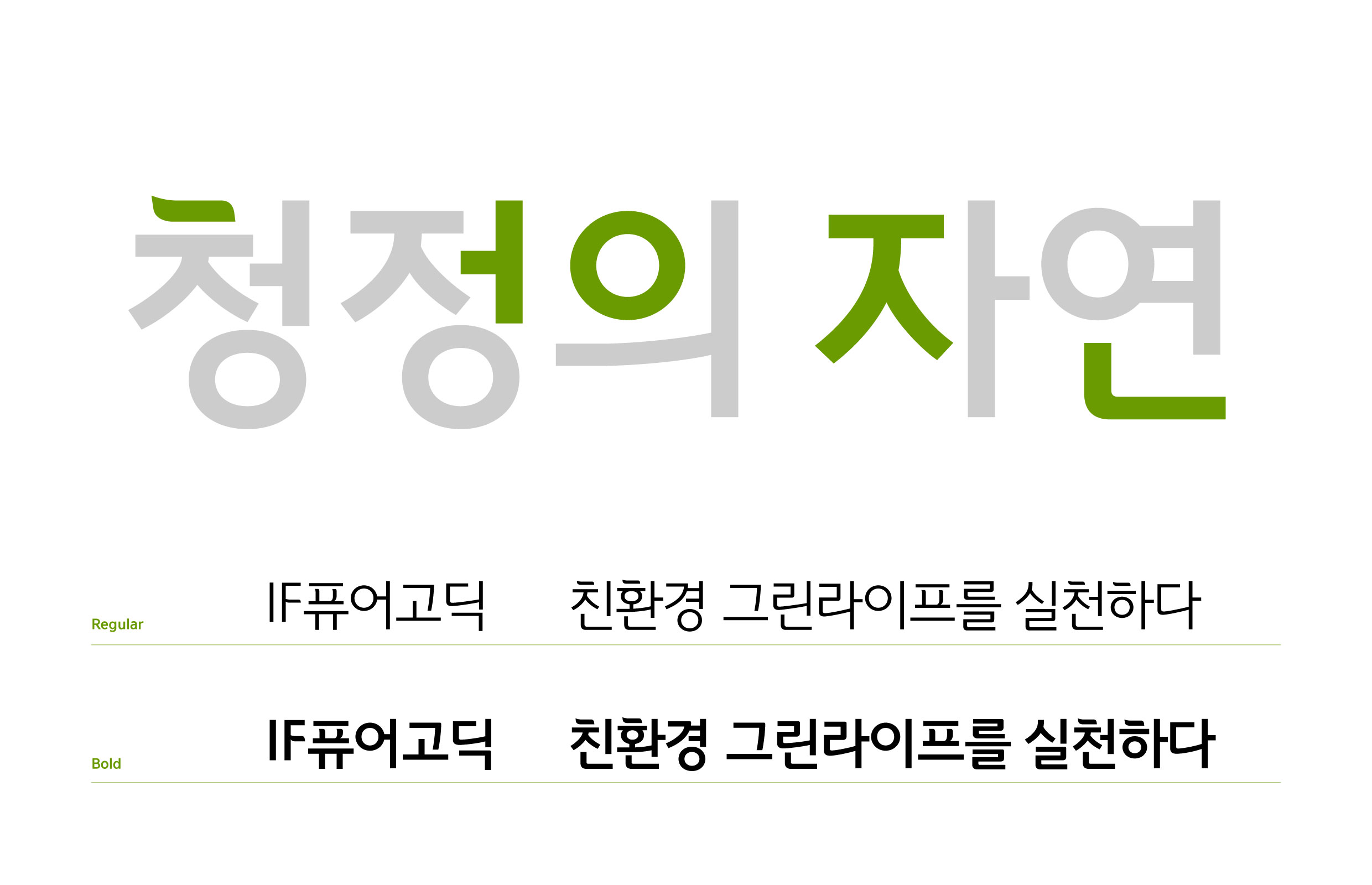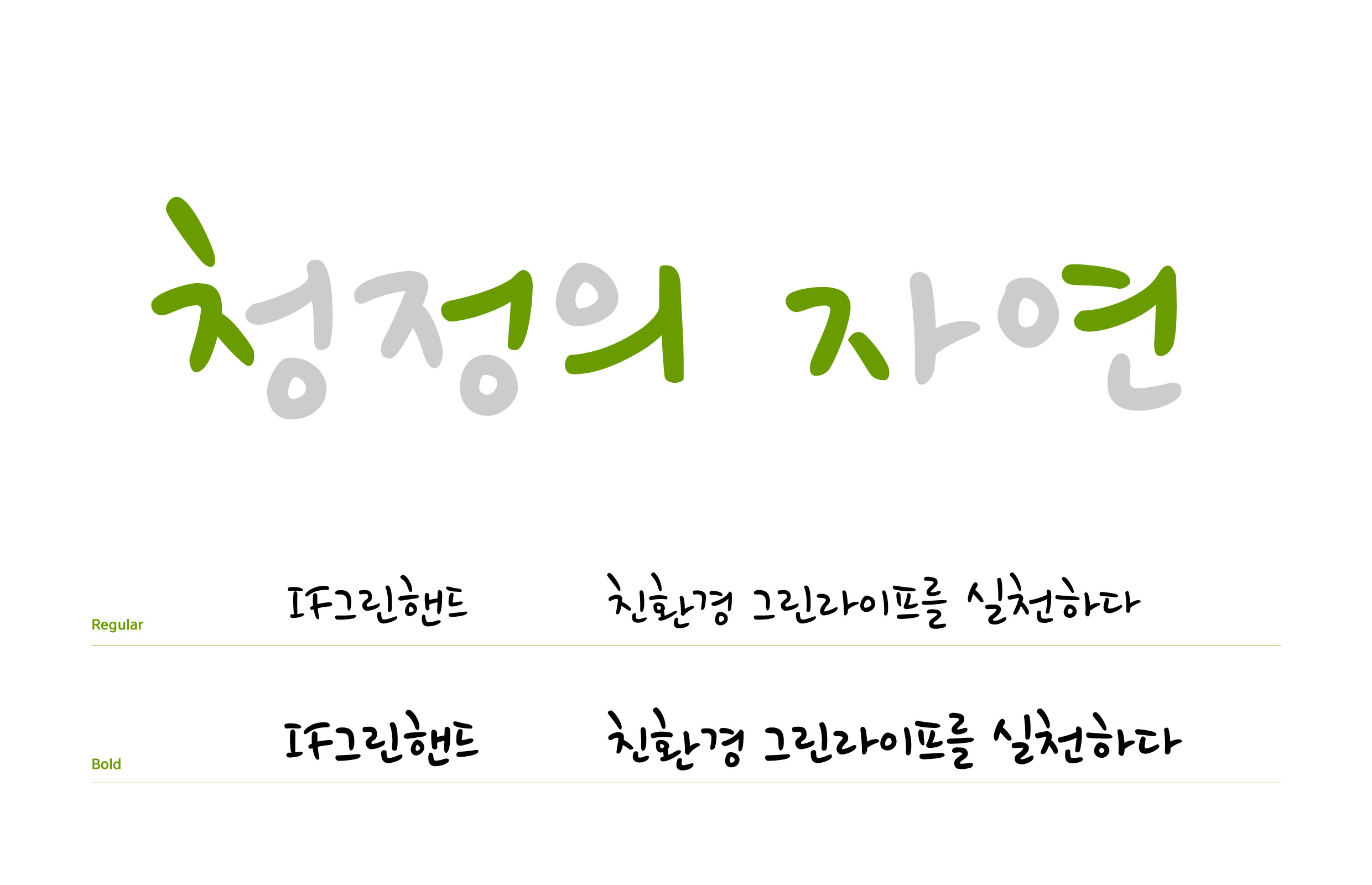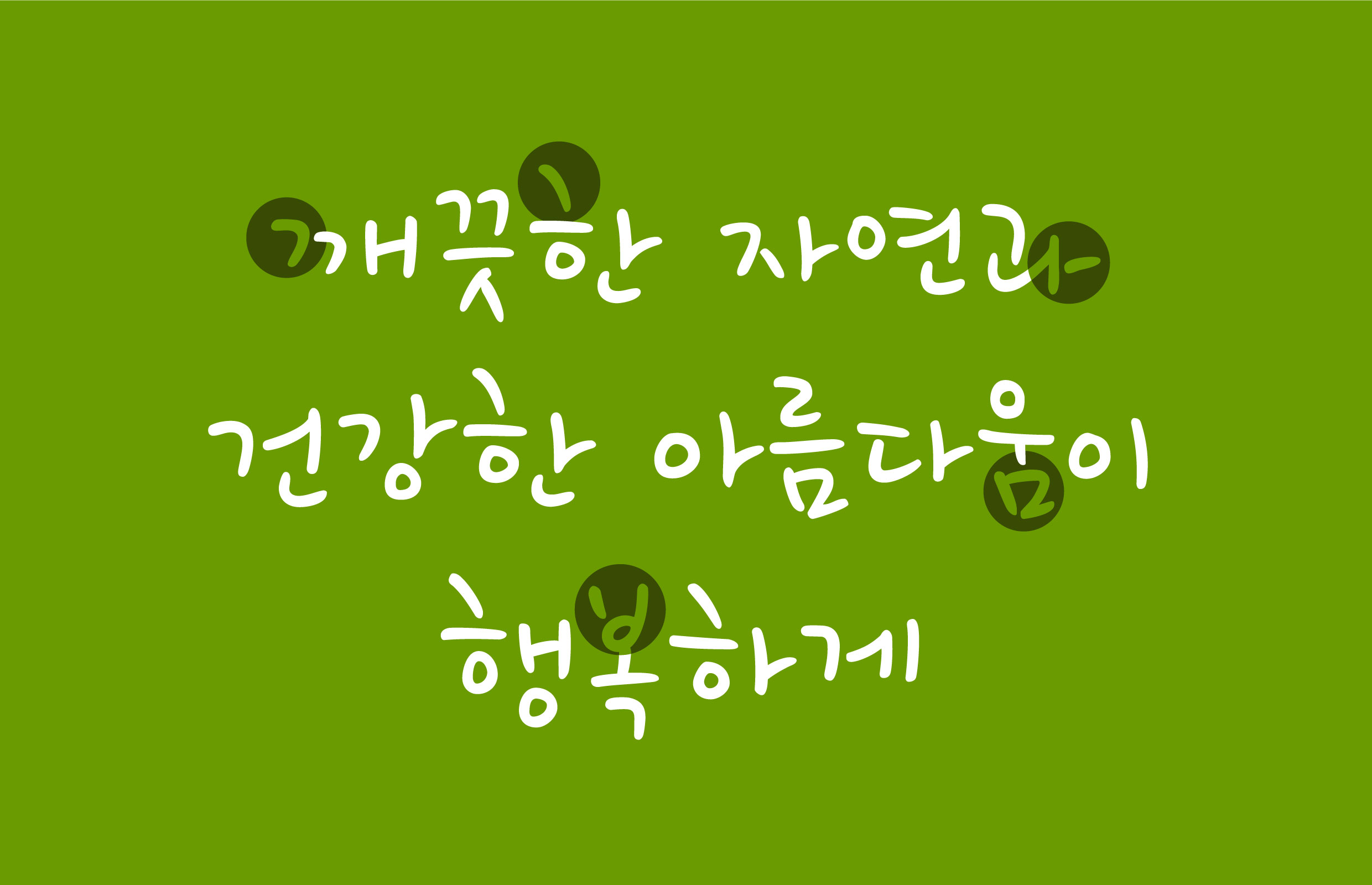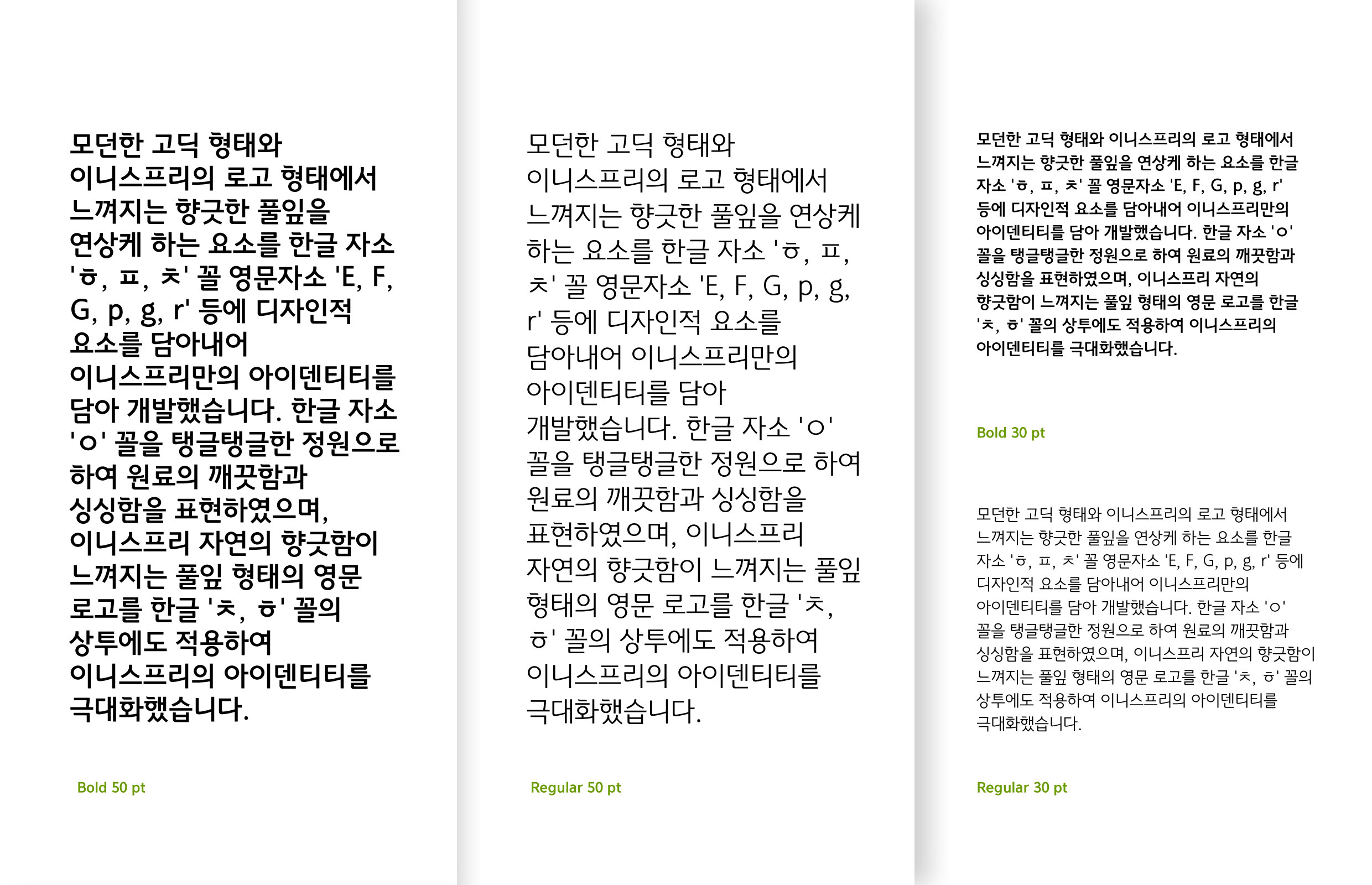
아모레퍼시픽 [if퓨어고딕·그린핸드]
맑고 깨끗한 느낌을 표현하고자 세리프가 없는 고딕 형태로 모던하게 디자인된 ‘퓨어고딕'은 모던한 자소에 향긋한 풀잎을 연상케 하는 디자인적 요소를 담아 이니스프리만의 아이덴티티를 담았다, '그린핸드'는 손글씨 형태로 디자인되어 이니스프리가 추구하는 순수하고 사랑스러운 느낌을 표현했다.